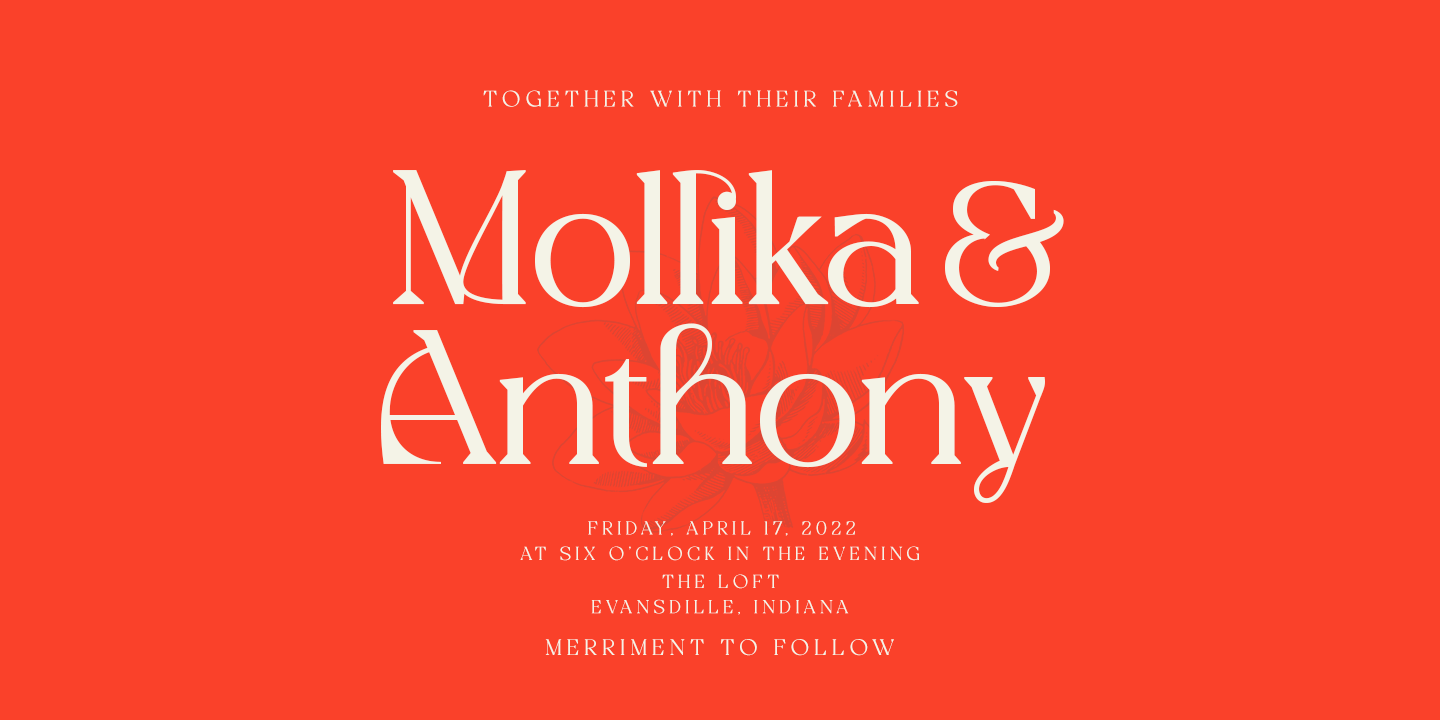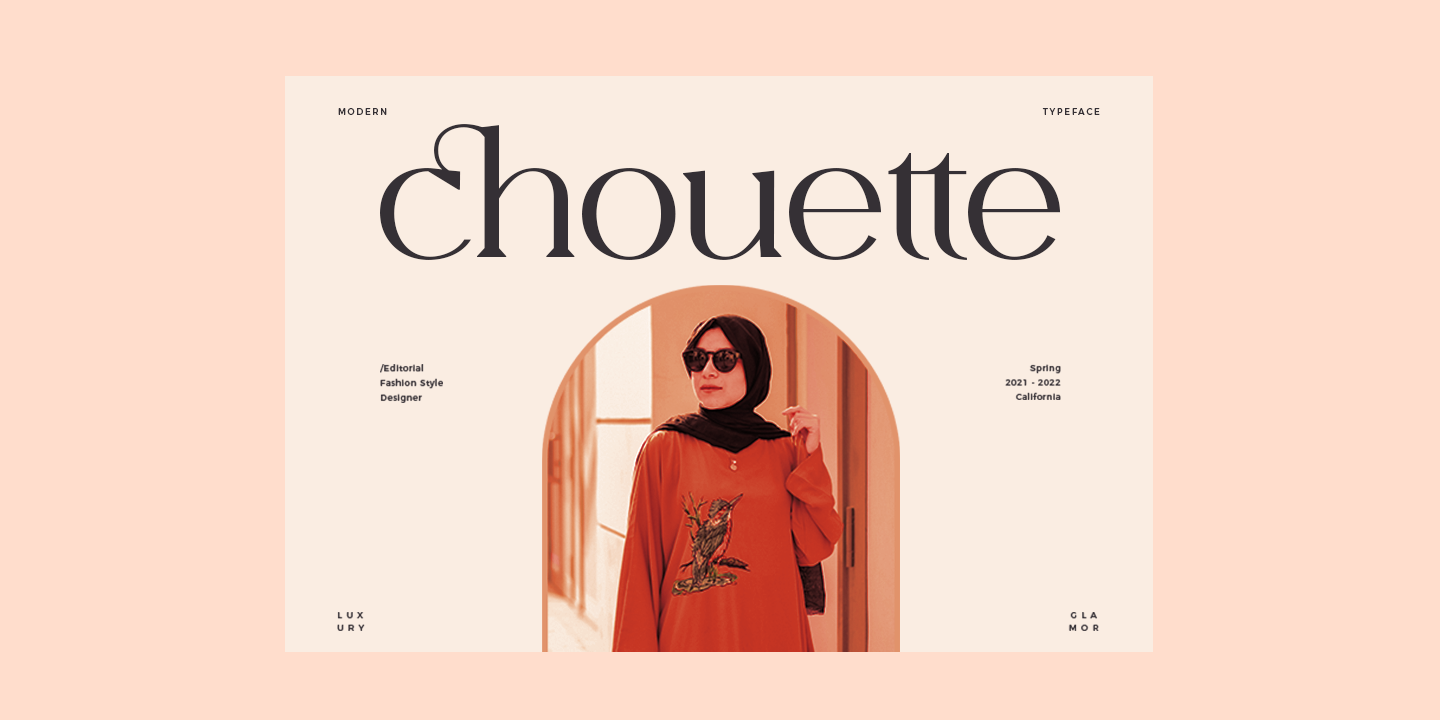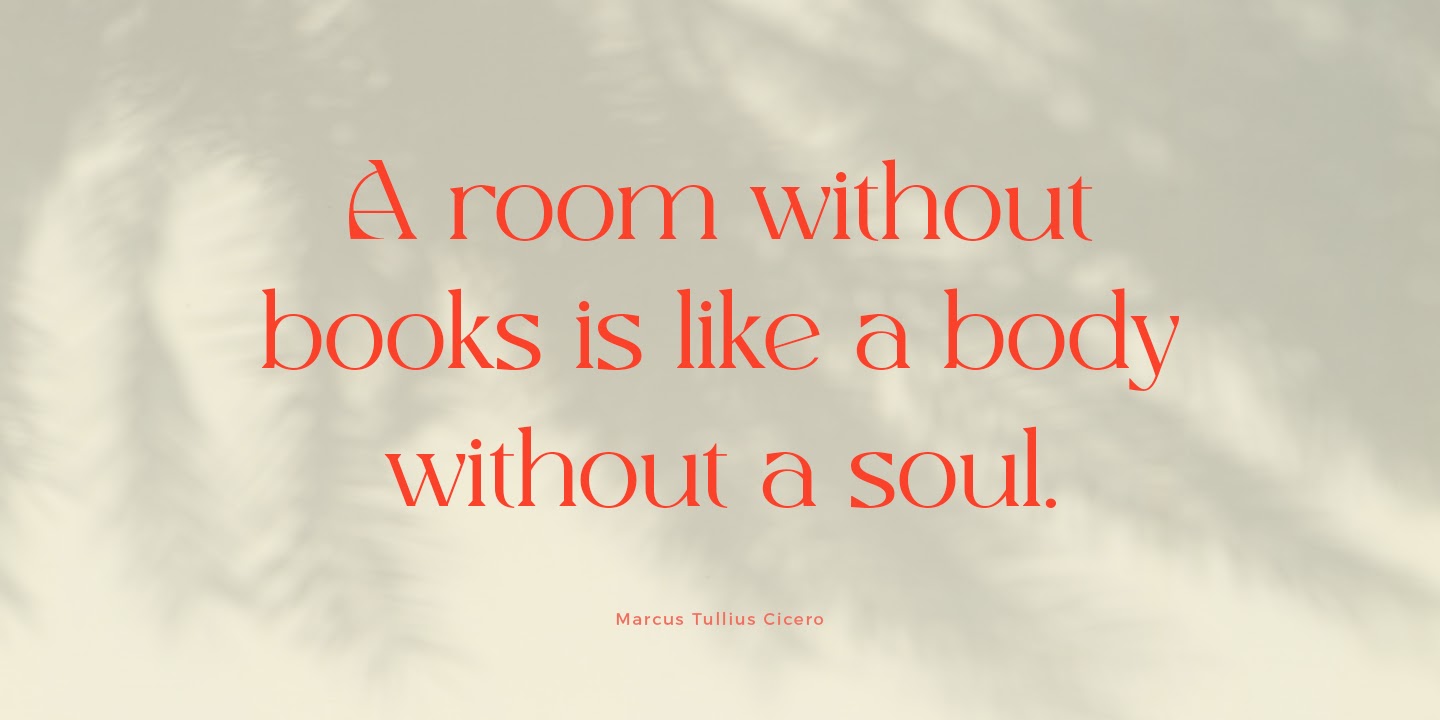
[Serif] Allogist Font – Font chữ khá đẹp
Allogist là một font serif thanh lịch mới sẽ tạo thêm nét sang trọng và các chấm kim cương sắc nét tạo thêm phong cách Ba Tư bóng bẩy nhưng dễ đọc.
Font chữ đa năng này hoàn hảo cho các dự án biên tập, tiêu đề tạp chí, thiết kế Logo, Thương hiệu quần áo, bao bì sản phẩm và thể hiện phẩm chất nam tính và nữ tính.
Allogist được trang bị chữ hoa, chữ thường, số và dấu chấm câu đầy đủ + Hỗ trợ đa ngôn ngữ và mã hóa PUA.
Đặc trưng:
• 3 Font weight
• Uppercase & Lowercase letters
• Alternative & Ligature Styles
• Numbers & Punctuation
Characters with accents
• Supports Multiple Languages